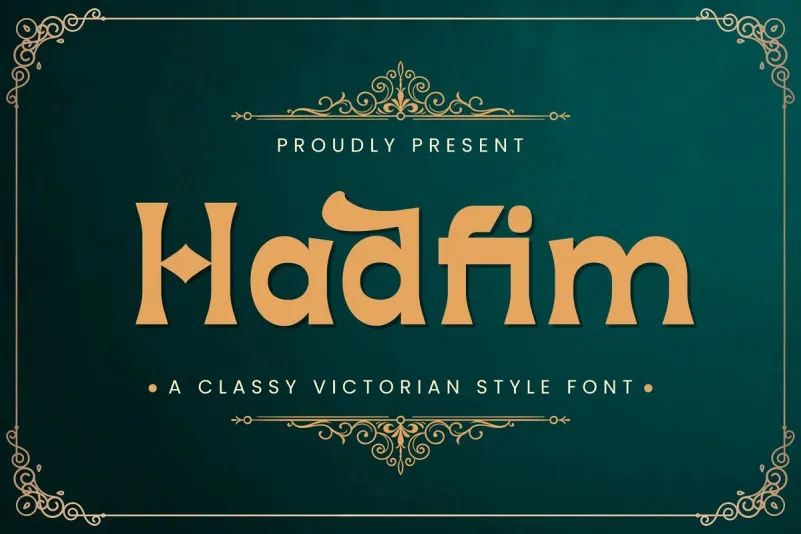
Hadfim Serif Font é uma nova tipografia serif inspirada nos selinhos vintage e emblemas das cervejarias. Criado por StringLabs, a fonte Hadfim oferece um design único, elegante e estiloso para os tempos de Victoriana. Seu formato curvado e detalhado será um recurso imprescindível em uma variedade de ambientes, desde sites de revistas até identidades corporativas. Com certeza, Hadfim irá transformar qualquer projeto em destaque, tornando-o ainda mais atraente e memorável. Ideal para adicionar um toque distintivo à sua próxima impressão ou design gráfico.